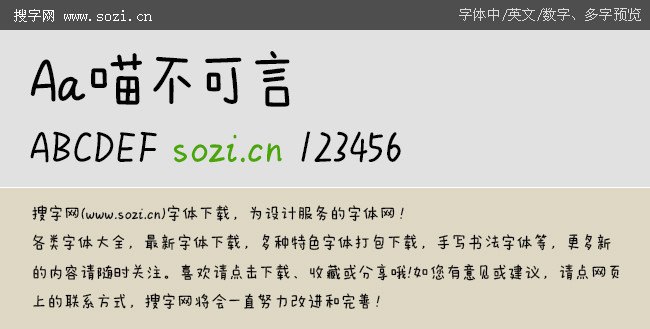
Aa喵不可言字體
搜字網(wǎng)給大家提供一款A(yù)a喵不可言字體中文字體下載,這是一款手寫風(fēng)格的卡通字體,字體充滿童趣,效果可愛大方,適合卡通海報設(shè)計、兒童包裝畫冊等宣傳廣告等應(yīng)用(此字體為個人非商用版,如需商用請聯(lián)系作者購買版權(quán))。